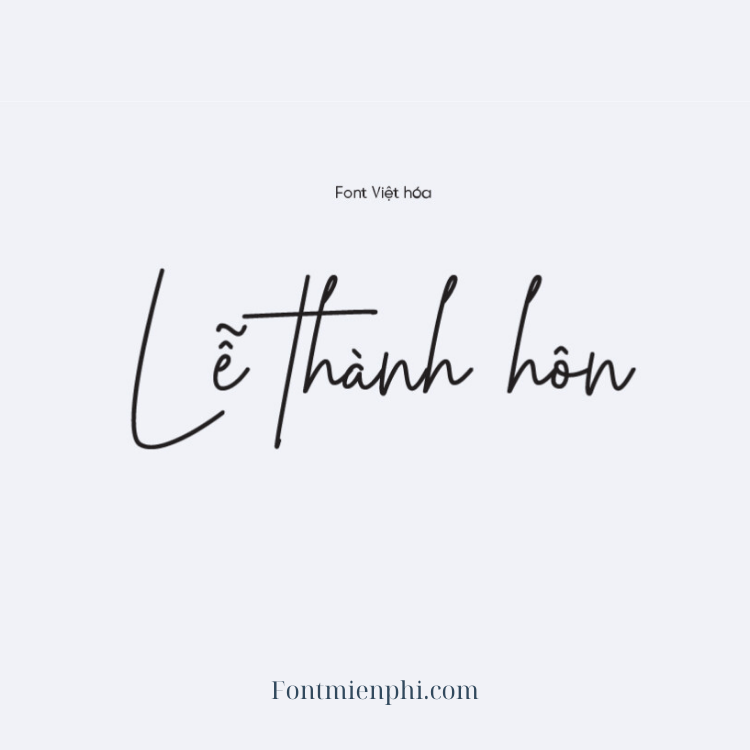
Font Việt hóa 1FTV VIP Katty Diona , Font thiệp cưới
Trong thế giới thiết kế đồ họa hiện đại, việc lựa chọn một Font Miễn Phí phù hợp đóng vai trò quan trọng trong việc truyền tải cảm xúc của tác phẩm. Font Việt hóa 1FTV VIP Katty Diona , Font thiệp cưới là một bộ phông chữ mang phong cách Script thư pháp hiện đại, được tối ưu hóa hoàn toàn cho bảng mã tiếng Việt. Với những đường nét thanh mảnh, uốn lượn mềm mại và tinh tế, bộ font này đã trở thành lựa chọn hàng đầu cho các nhà thiết kế đang tìm kiếm sự sang trọng và khác biệt cho các ấn phẩm in ấn quan trọng.
Ưu điểm nổi bật của Font Việt hóa 1FTV VIP Katty Diona , Font thiệp cưới
Lý do khiến bộ font này được ưa chuộng chính là sự kết hợp hoàn hảo giữa tính thẩm mỹ và tính ứng dụng cao trong thực tế thiết kế hằng ngày.
Nét chữ nghệ thuật và tính ứng dụng đa dạng
Font Việt hóa 1FTV VIP Katty Diona , Font thiệp cưới sở hữu các ký tự đặc biệt với đuôi chữ dài, giúp tạo điểm nhấn ấn tượng cho các dòng tiêu đề. Bạn có thể sử dụng font này để thiết kế bìa sách, logo thương hiệu thời trang, hoặc các loại thiệp mời cao cấp. Đặc biệt, bộ font đã được căn chỉnh khoảng cách chữ tỉ mỉ, giúp việc gõ tiếng Việt không bị lỗi dấu, giữ được vẻ đẹp tự nhiên nhất của từng con chữ trên các phần mềm đồ họa chuyên nghiệp.
Lựa chọn hoàn hảo cho thiết kế đám cưới
Đối với các cặp đôi và đơn vị in ấn, tìm kiếm một font chữ thể hiện được sự lãng mạn là điều tiên quyết. Bộ font này đáp ứng tốt yêu cầu đó nhờ phong cách viết tay uyển chuyển, tạo nên cảm giác gần gũi nhưng không kém phần trang trọng cho ngày trọng đại.
Kết luận về bộ font chữ cao cấp
Việc sử dụng Font Miễn Phí, Font Việt Hóa, Font Việt hóa 1FTV VIP Katty Diona , Font thiệp cưới sẽ giúp nâng tầm các sản phẩm thiết kế của bạn lên một đẳng cấp mới. Với sự hỗ trợ đầy đủ tiếng Việt và phong cách nghệ thuật độc đáo, đây chắc chắn là công cụ không thể thiếu trong bộ sưu tập của mọi designer chuyên nghiệp tại Việt Nam hiện nay.